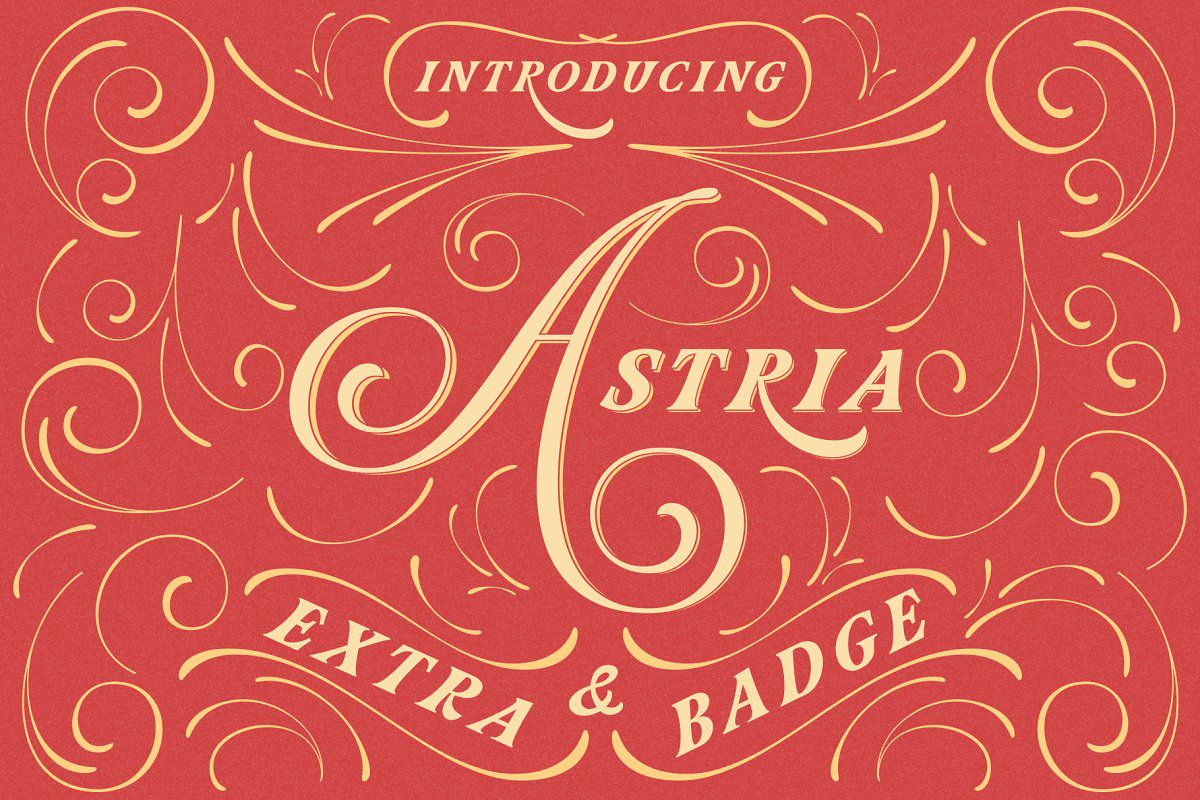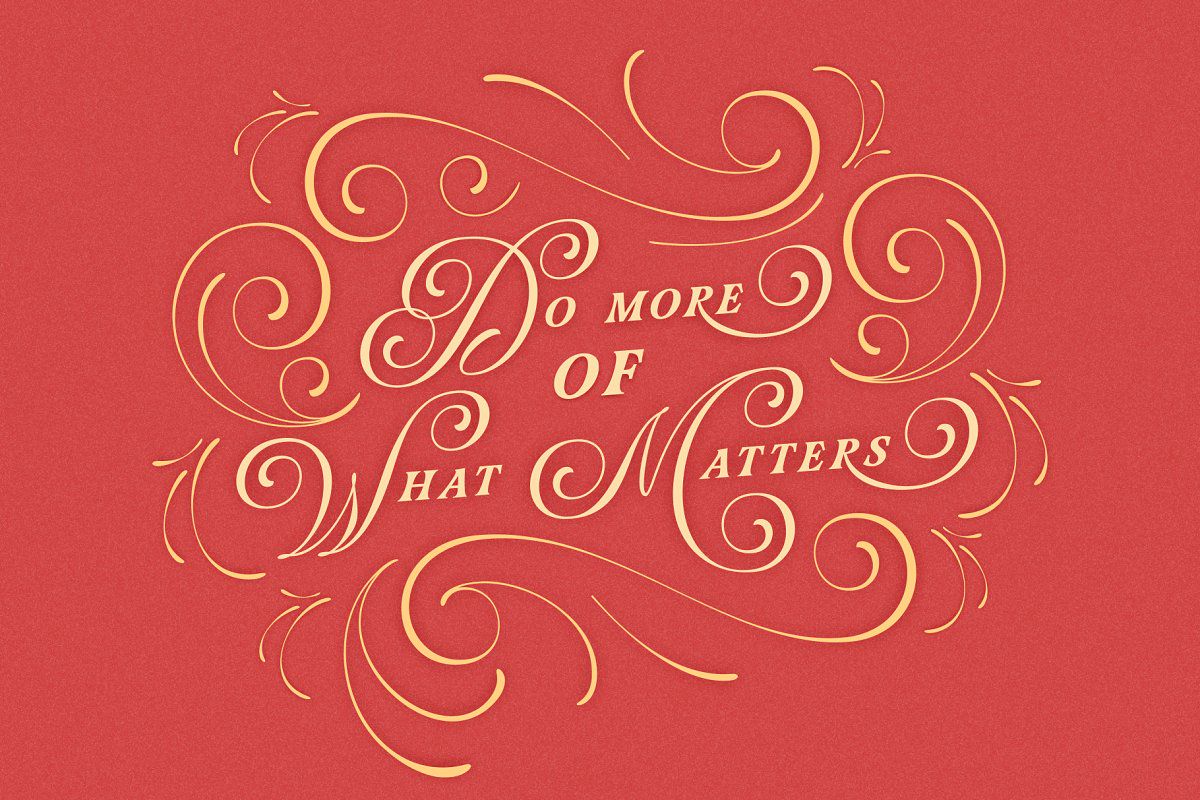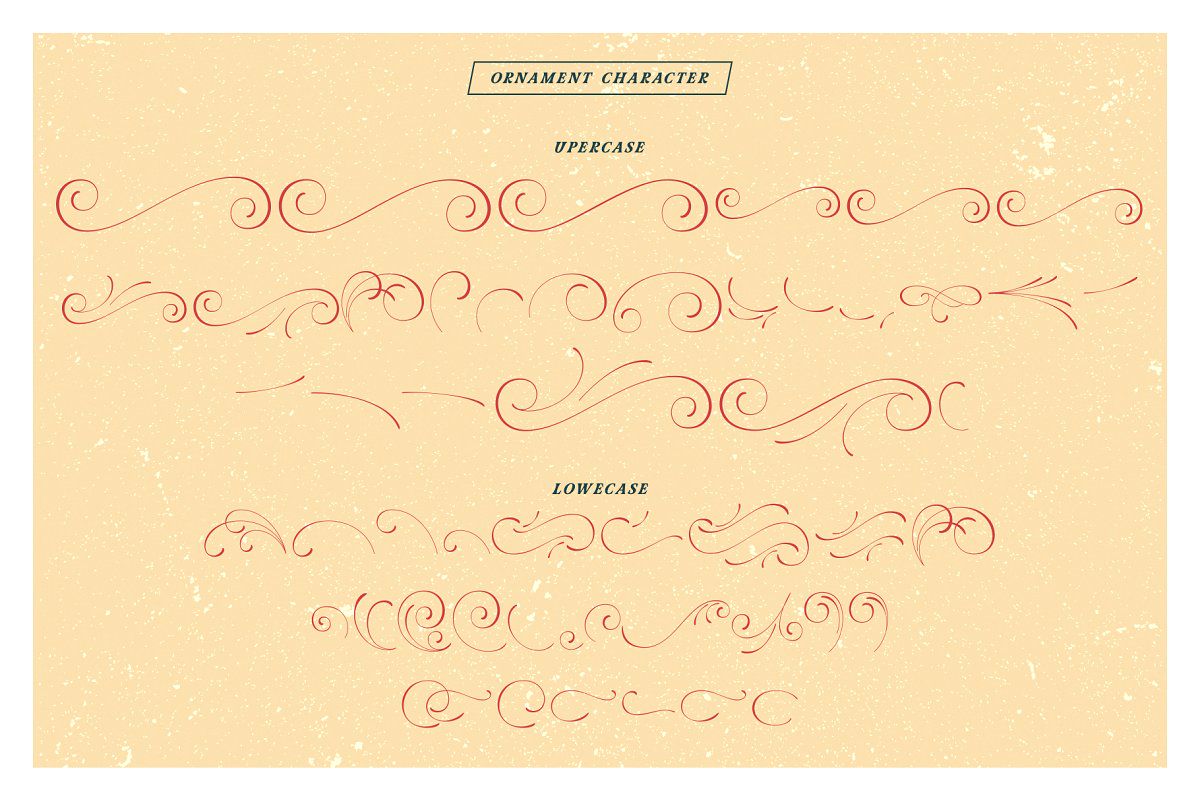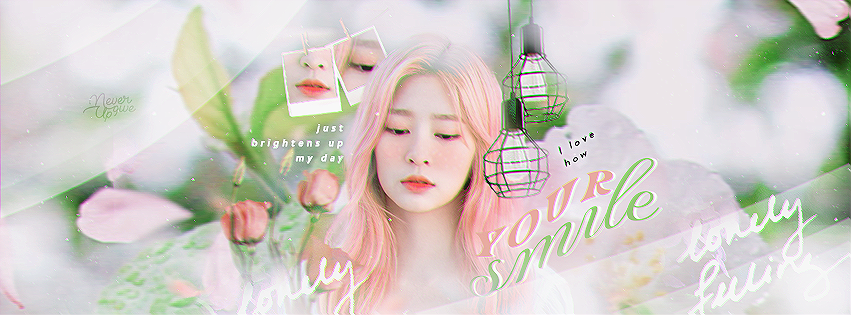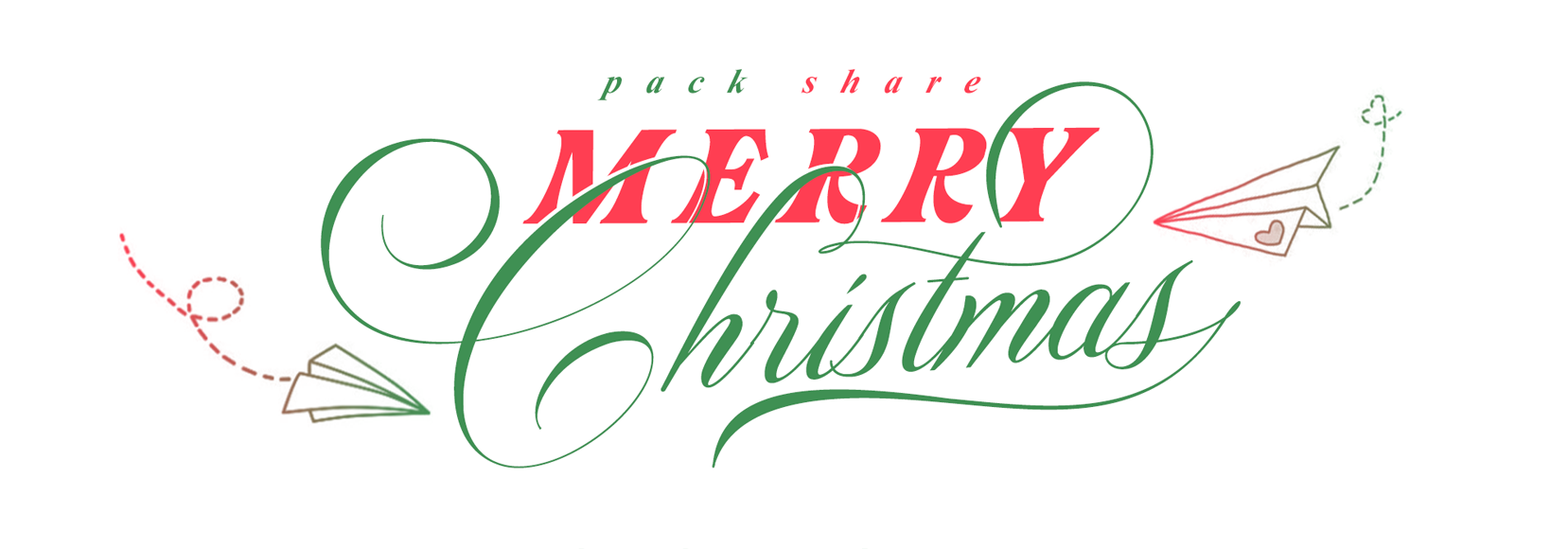
[FONT] Astria
Lại là một font khác mình tải trên Creative Market đây :3 Font này siu xinh yêu và dễ kết hợp với các font dạng Script khác nữa
Typeface: Display